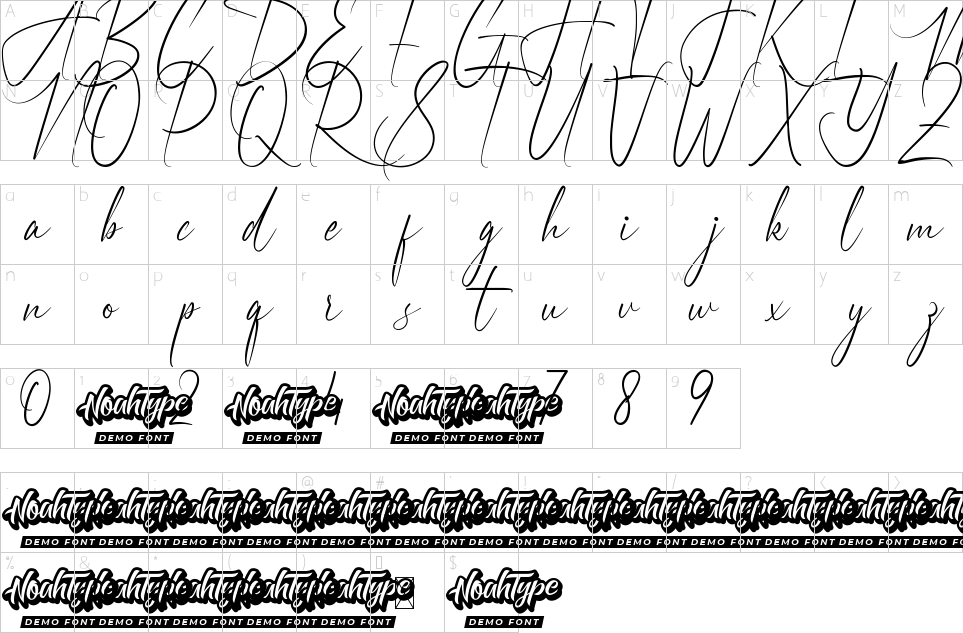
Arthur Dale Font
A fonte Arthur Dale é uma escolha suave e versátil para projetos gratuitos em Windows e Mac. Ela foi criada por um designer não informado e tem se destacado por sua elegância, tornando-a uma excelente opção para designers que buscam uma fonte moderna e minimalista. Com uma alta popularidade, já foi baixada 2.568 vezes, demonstrando sua adequação e qualidade. Se você está buscando uma fonte clara e fácil de ler que se adapta bem em diversos contextos, Arthur Dale pode ser a escolha perfeita para seus projetos gratuitos.
Mapa de caracteres da fonte Arthur Dale Font